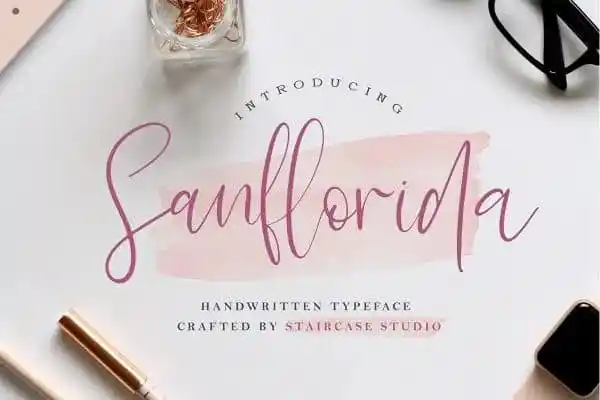
A Sanflorida Script é uma fonte script elegante com um toque divertido que se destaca na categoria de fontes scripts para projetos digitais e impressos. Criada para atender a necessidades multilíngues, essa fonte oferece mais de 440 caracteres gílico, garantindo flexibilidade e variedade em cada projeto. Esta elegante escolha gráfica é perfeita para criar um design único para seus cartões de casamento, identidade visual, convites, citações, impressões personalizadas, tipografia e muito mais. A Sanflorida Script não apenas oferece uma cara retrô e sofisticada com suas linhas curvas delicadas e traços fluidos, mas também permite que você dê um toque divertido de inovação a qualquer projeto. Suas linhas sutis e sua personalidade única tornam essa fonte uma escolha ideal para designers em busca de algo que destoe do monótono.